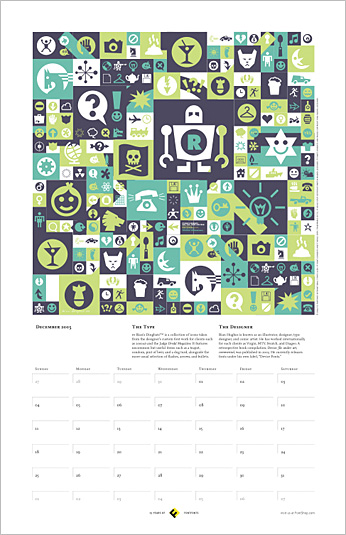
Kalenderblatt: Rian Hughes’ piktografischer DezemberDas letzte Blatt unseres FontFont-Wandkalenders 2005,
gestaltet von Rian Hughes mit seiner Piktogramm-Sammlung FF Rian’s
Dingbats. Der Londoner Illustrator und Comic-Zeichner veröffentlichte seit
1993 seine retro-futuristischen Schriften in der FontFont-Bibliothek, zum
Beispiel FF Revolver, FF Knobcheese und FF CrashBangWallop. Weiterlesen und PDF laden ...
![]() Rian Hughes über seine Symbolsammlung: »FF Rian’s Dingbats
ist eine Sammlung von Kommunikationssymbolen, die bei der Erstellung von
Spezialschriften für Kunden wie 2000AD und dem Judge Dredd
Magazine entstanden sind. Das Schriftpaket besteht aus 4 Schnitten und
enthält so nützliche Piktogramme wie eine Teekanne, Kondome,
Bierkrüge, bissige Hunde, zahme Katzen oder dampfende
Sch...haufen.«